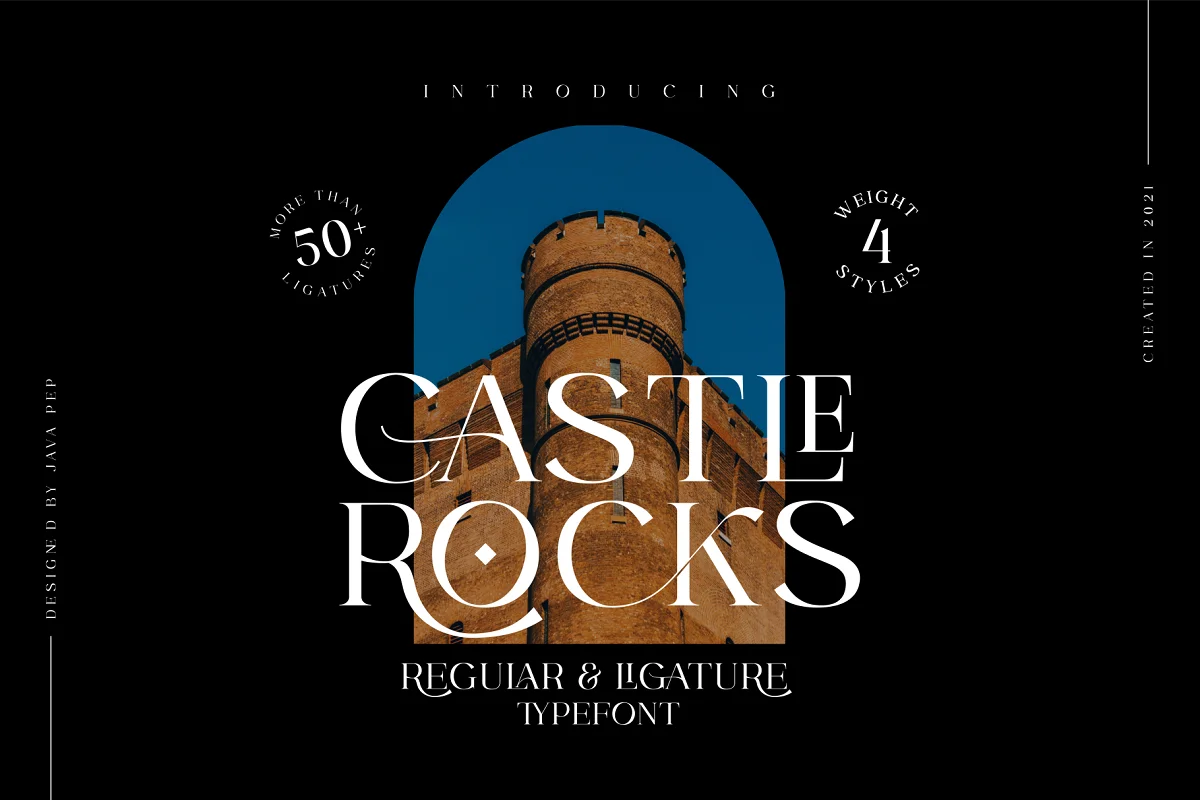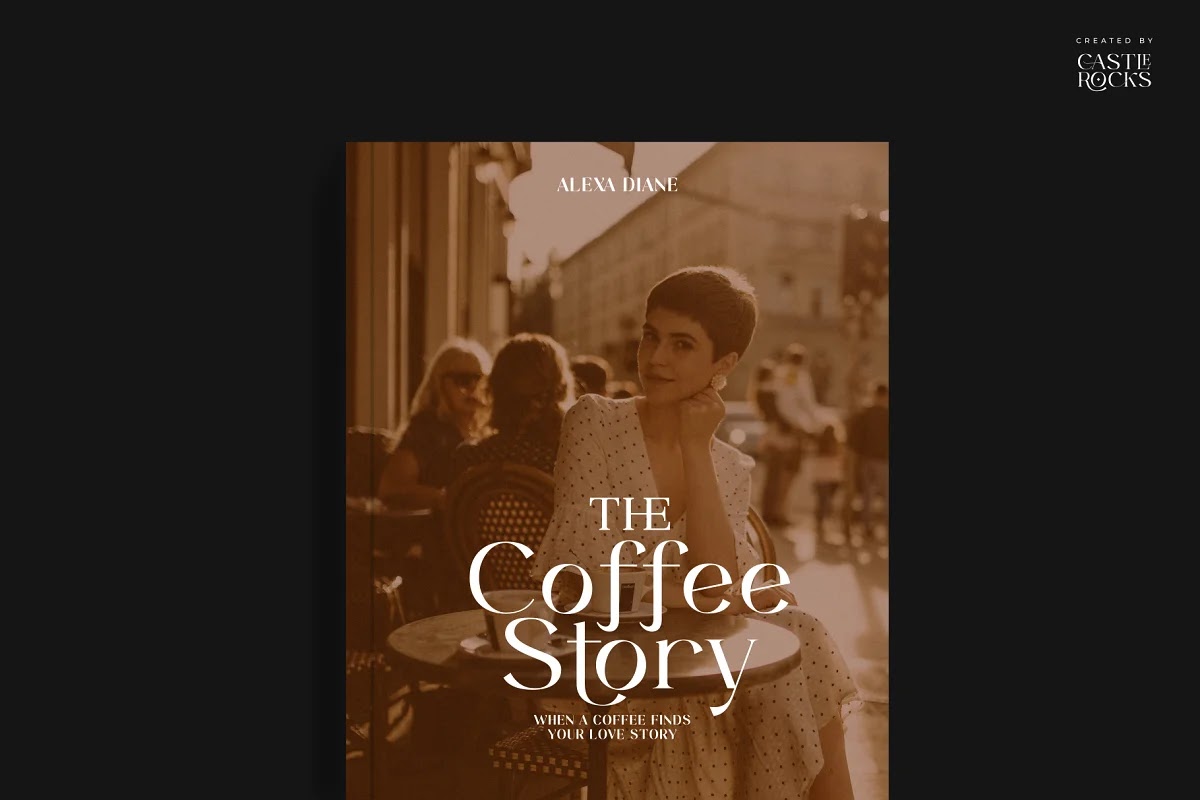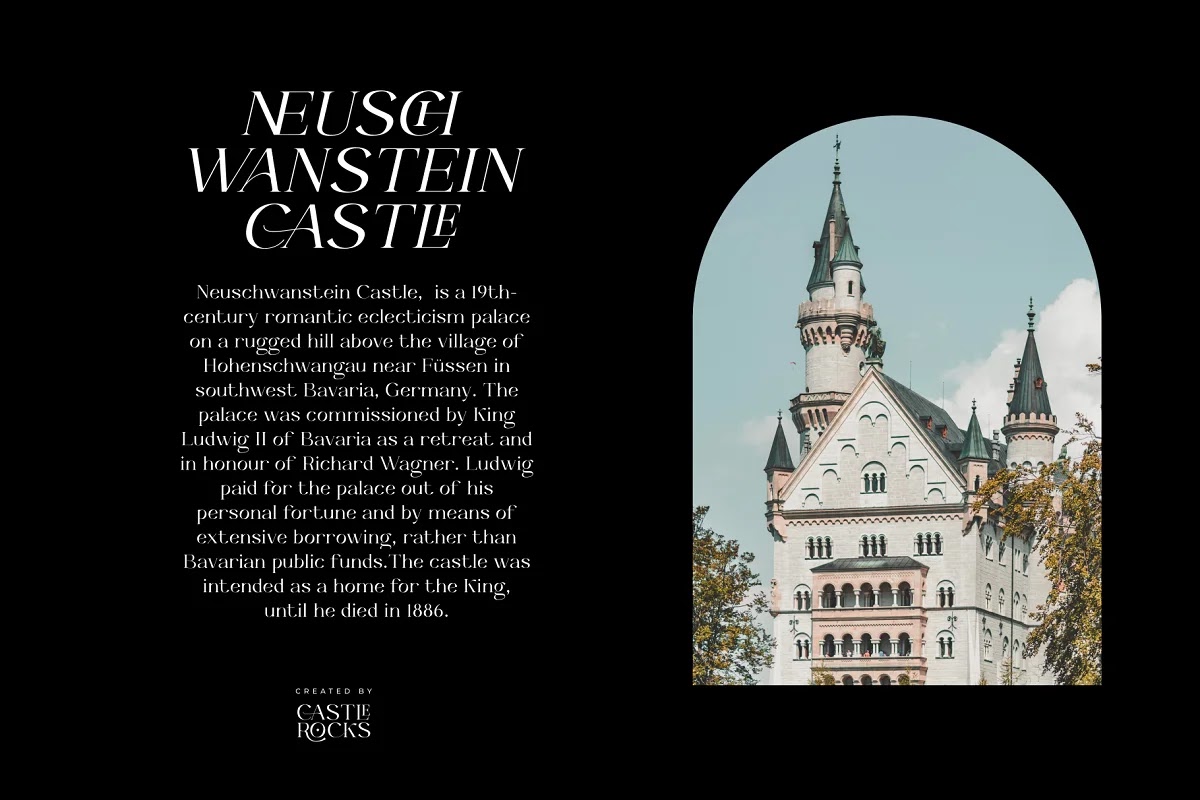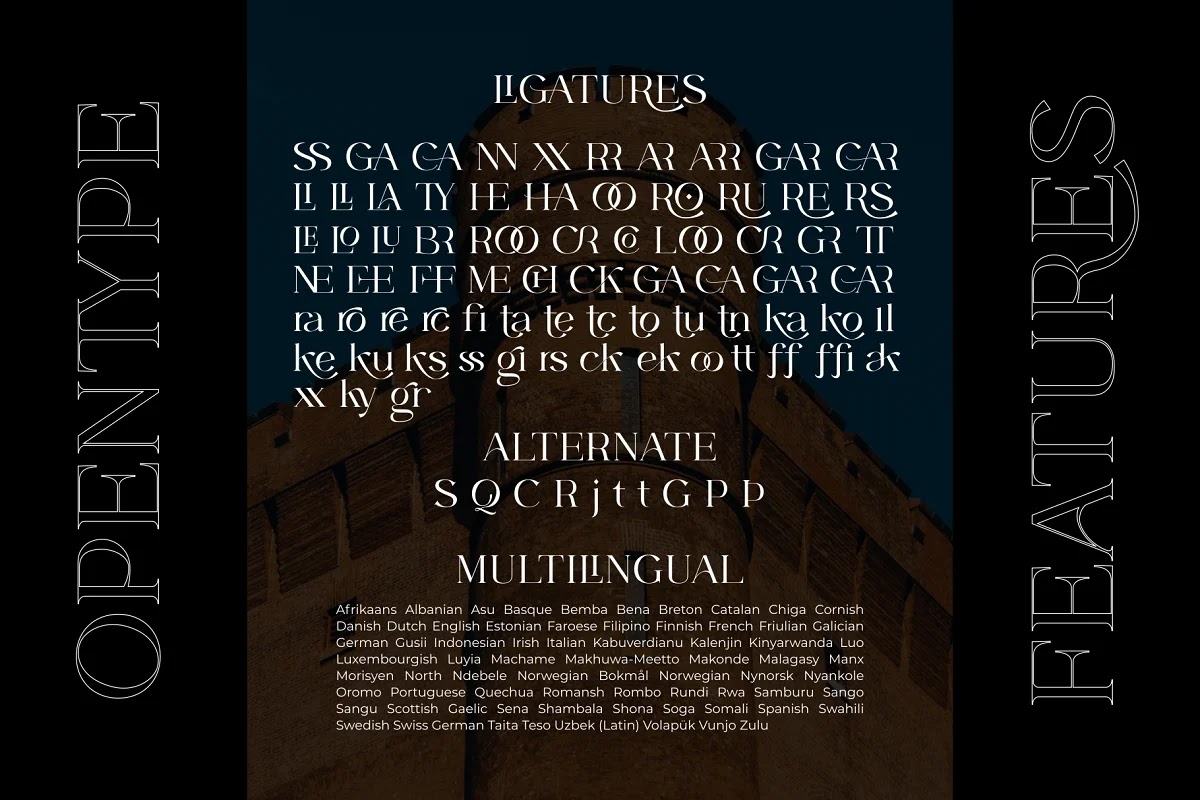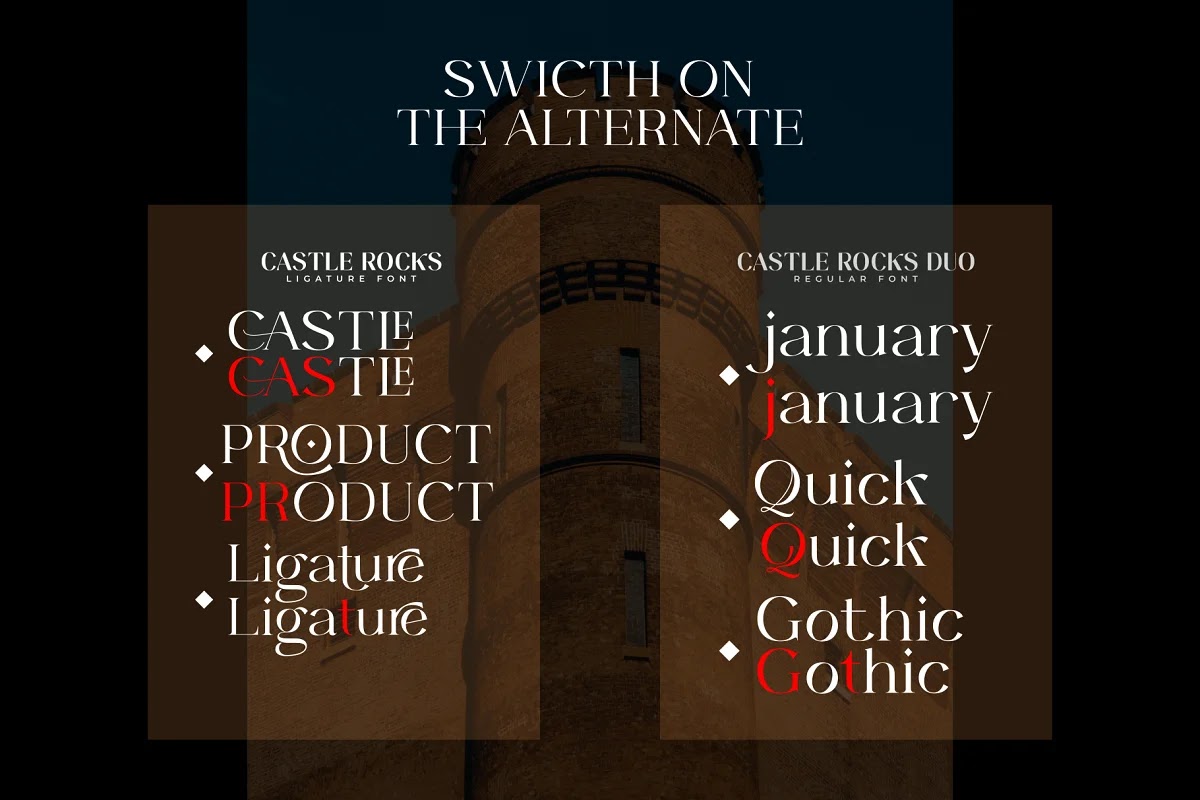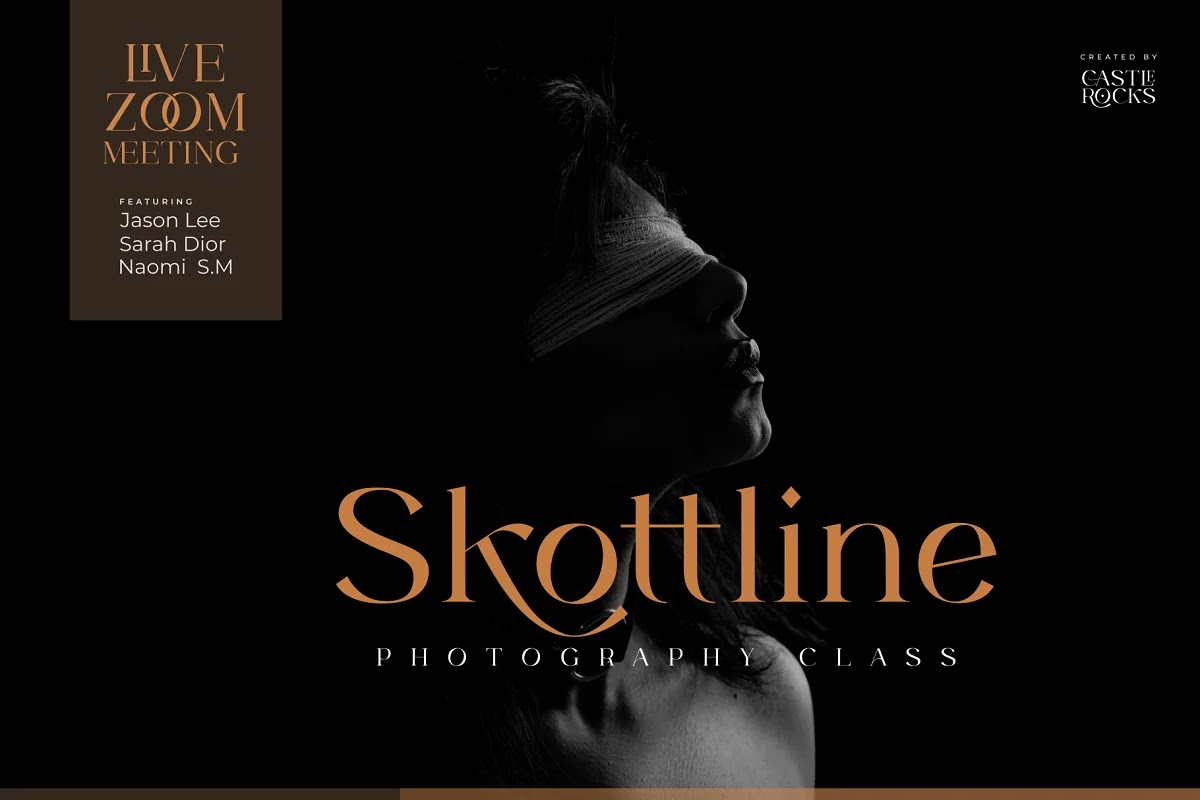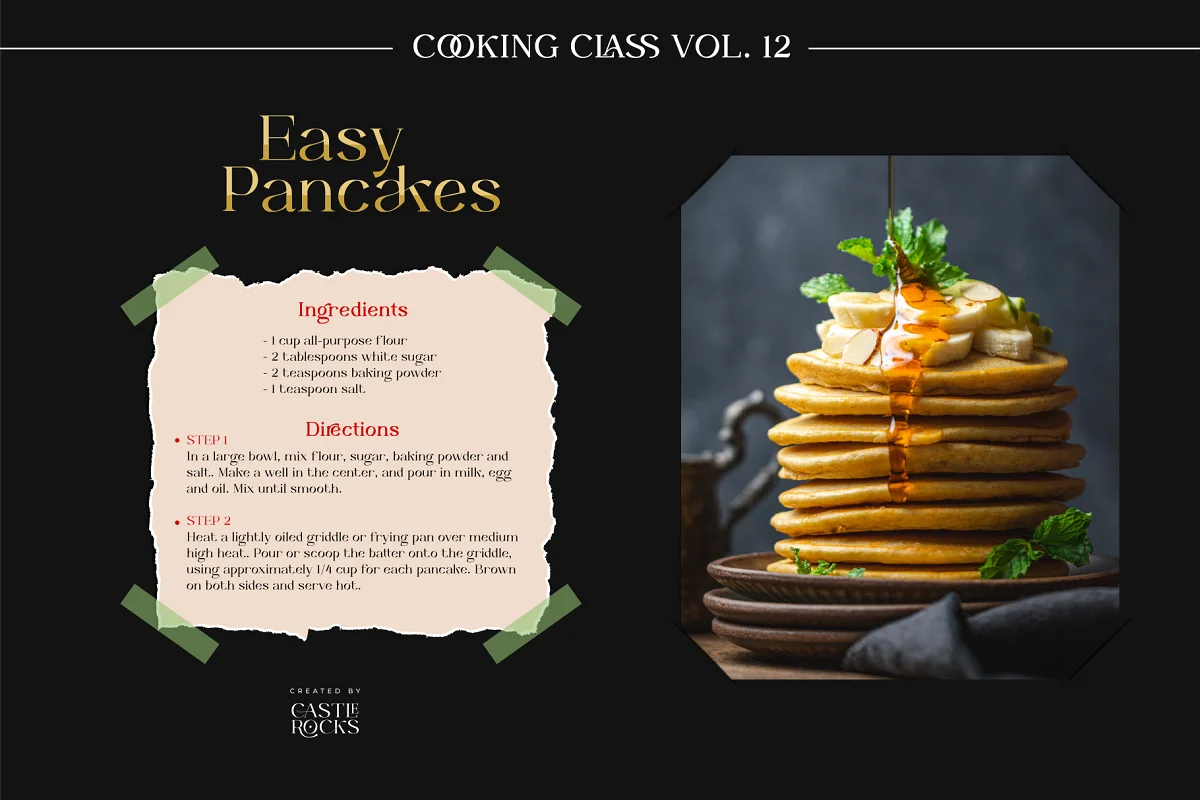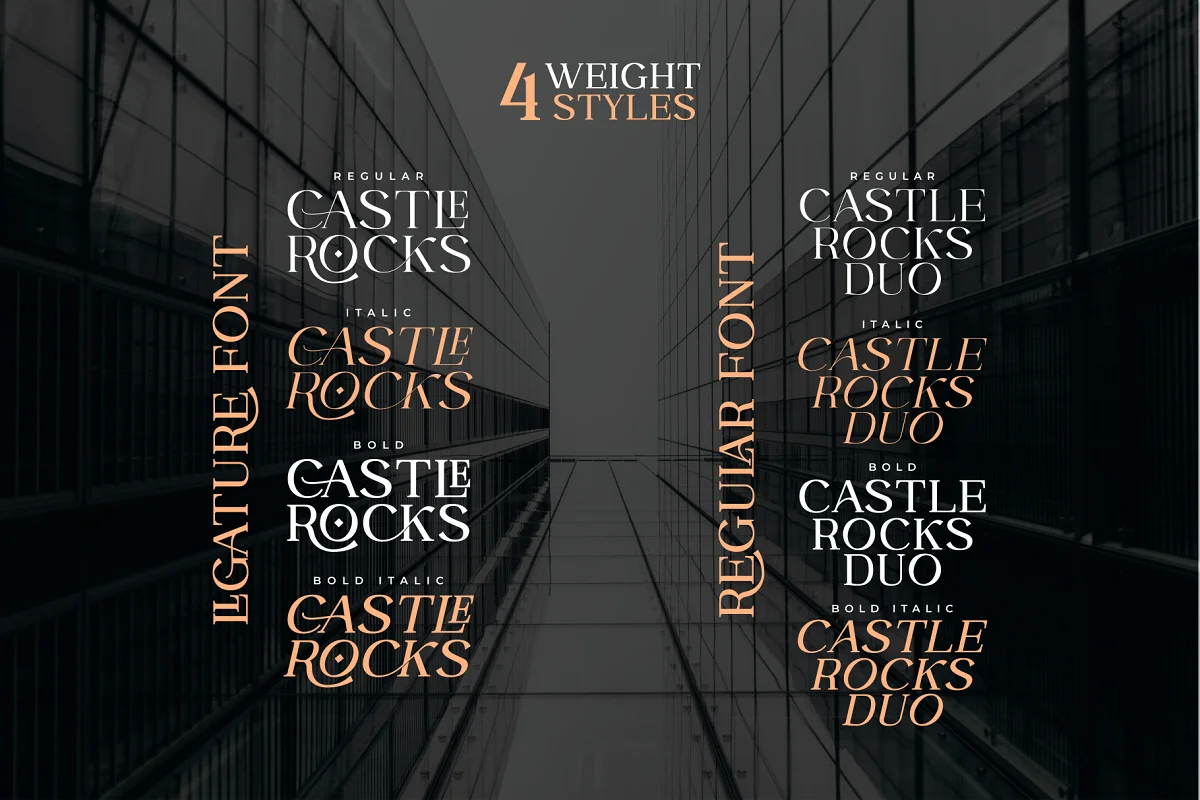
Giới thiệu font chữ serif ghép nối được gọi là phông chữ CASTLE ROCKS duo, font chữ này có hơn 50 chữ ghép bao gồm đầy đủ cả chữ hoa và chữ thường.
Gói này bao gồm CASTLE ROCKS là phông chữ ghép và CASTLE ROCKS DUO là phông chữ thông thường để bạn có thể kết hợp nó để kết hợp với việc chuyển đổi phông chữ ghép (CASTLE ROCKS) hoặc phông chữ thông thường (Castle Rock). CASTLE ROCKS duo font là những phông chữ đẹp và trang nhã, hoàn hảo cho tiêu đề, dòng tiêu đề, biểu trưng, thương hiệu cá nhân, lời mời, xây dựng thương hiệu, trích dẫn, tạp chí, font chữ văn bản, v.v.
• CASTLE ROCKS (Phông chữ ghép), font chữ ghép bộ đầy đủ này ở dạng chữ hoa và chữ thường và có 4 kiểu regular, italic, bold, và bold italic.
• CASTLE ROCKS DUO (Phông chữ thông thường), font chữ thông thường này không có tính năng ghép nối để bạn có thể kết hợp với CASTLE ROCKS hoặc sử dụng để làm font chữ văn bản, phông chữ này có 4 kiểu chữ regular, italic, bold, và bold italic.
• Đa ngôn ngữ , hỗ trợ hơn 30 ngôn ngữ